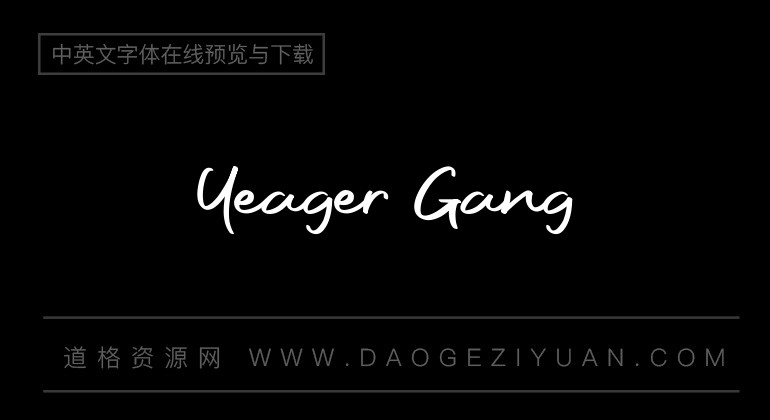
Yeager Gang 是一种非常受欢迎的手写风格字体,特别受到年轻人的青睐。它的特点是线条粗细不一,笔画有些潦草,排版整齐但不规则,给人一种个性化和随意的感觉。Yeager Gang 字体的字体家族包括 Yeager Regular 和 Yeager Clean 两种字体风格,可以满足不同场合和风格的需求。Yeager Gang 字体现在已经成为了许多设计师、艺术家和创意人士的首选字体之一,被广泛应用于各种设计、广告、海报、标志、包装和宣传材料等领域。内容介绍
Yeager Gang是一款非常不错的手写艺术字体,具有很好的视觉感,适合于文化类的宣传设计、商业类品牌的广告和产品包装设计以及个性化文字排版等较多场景。